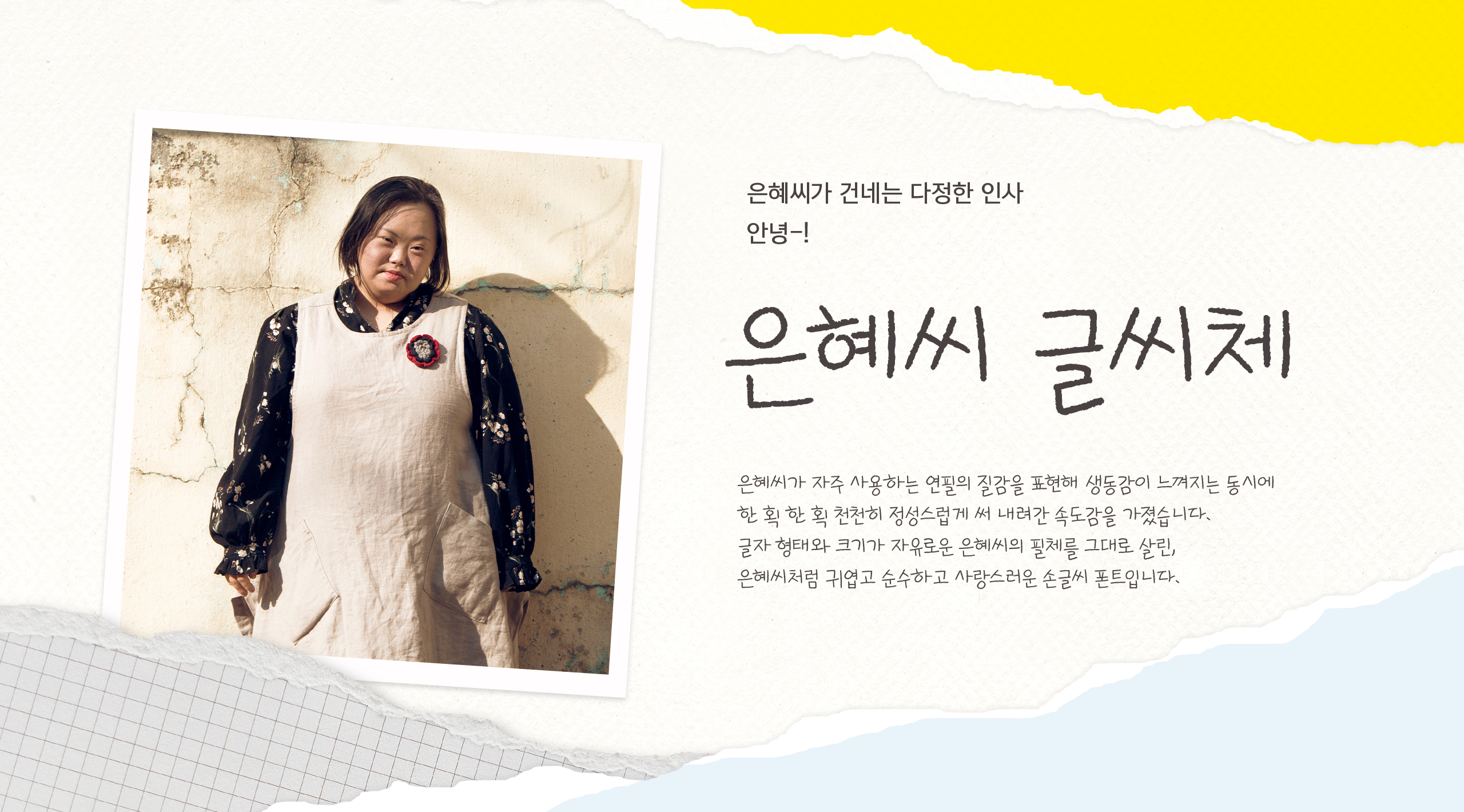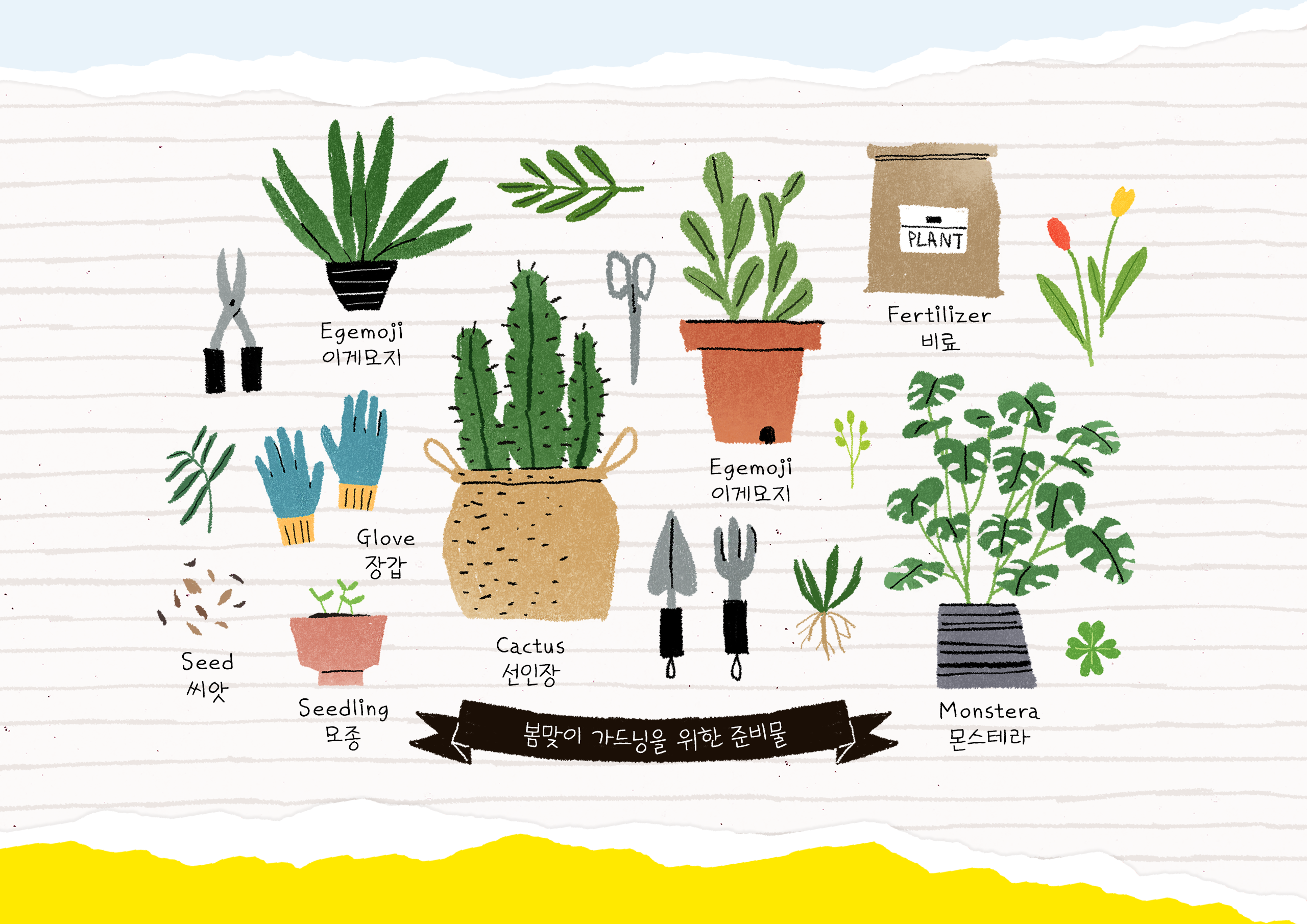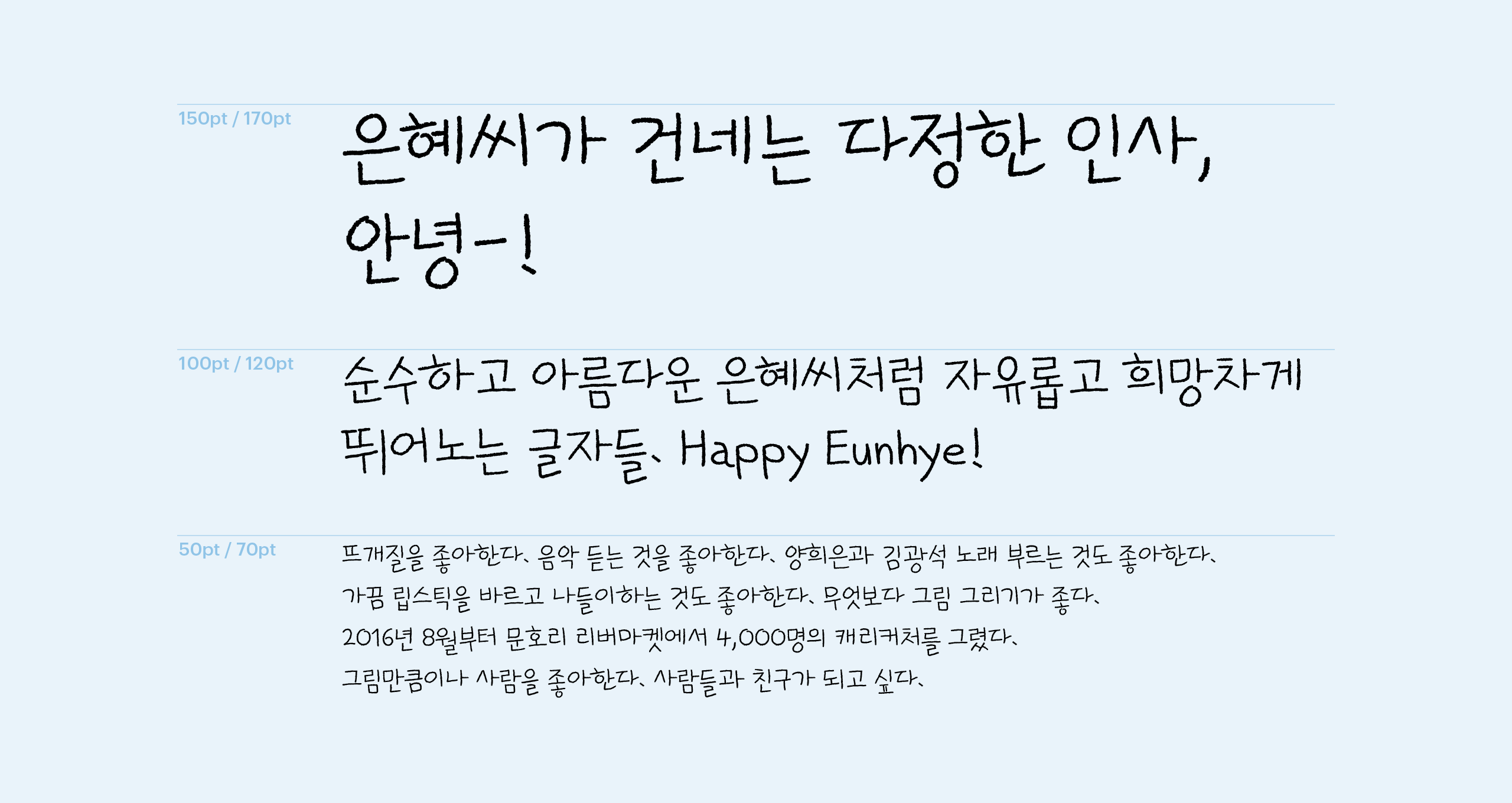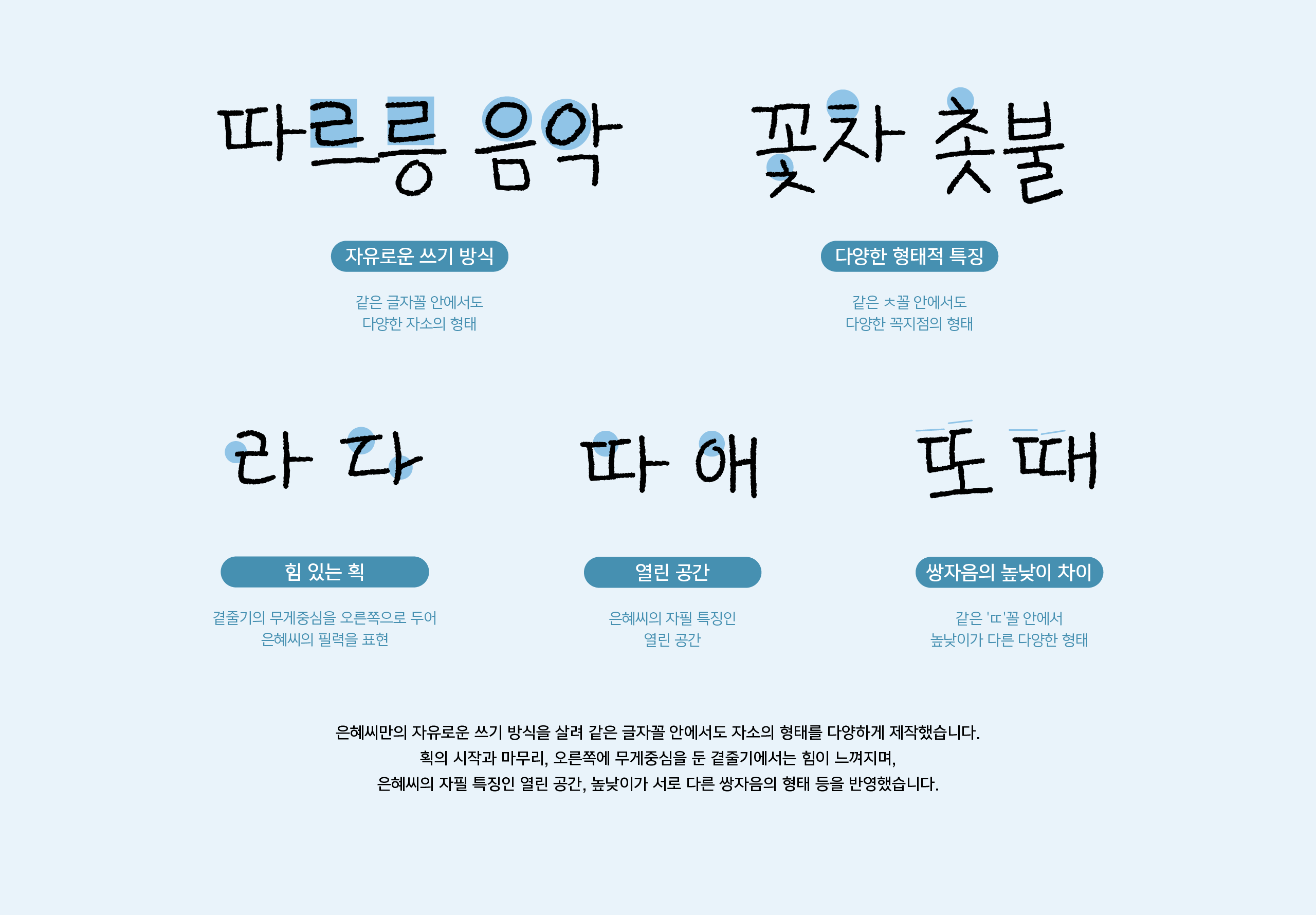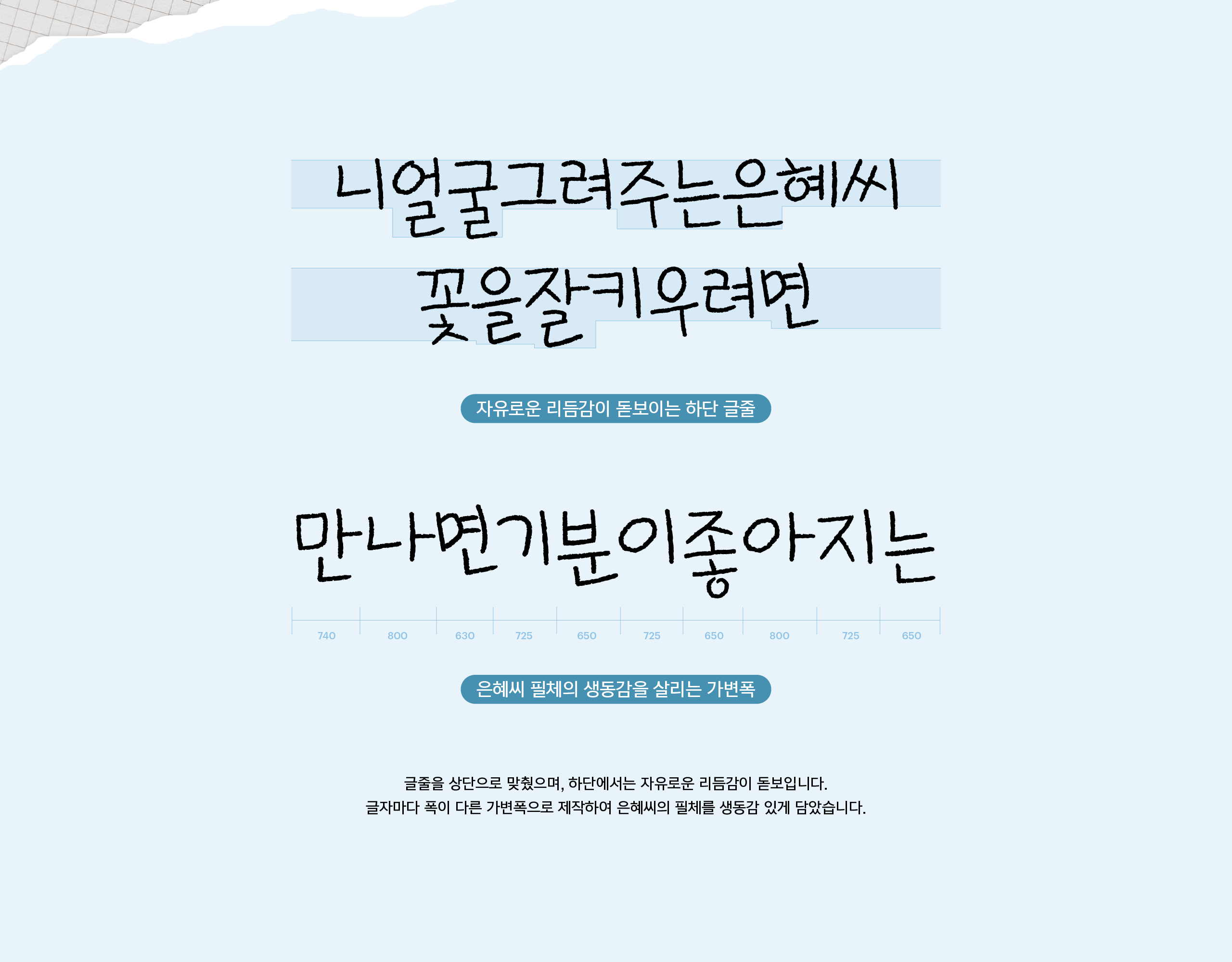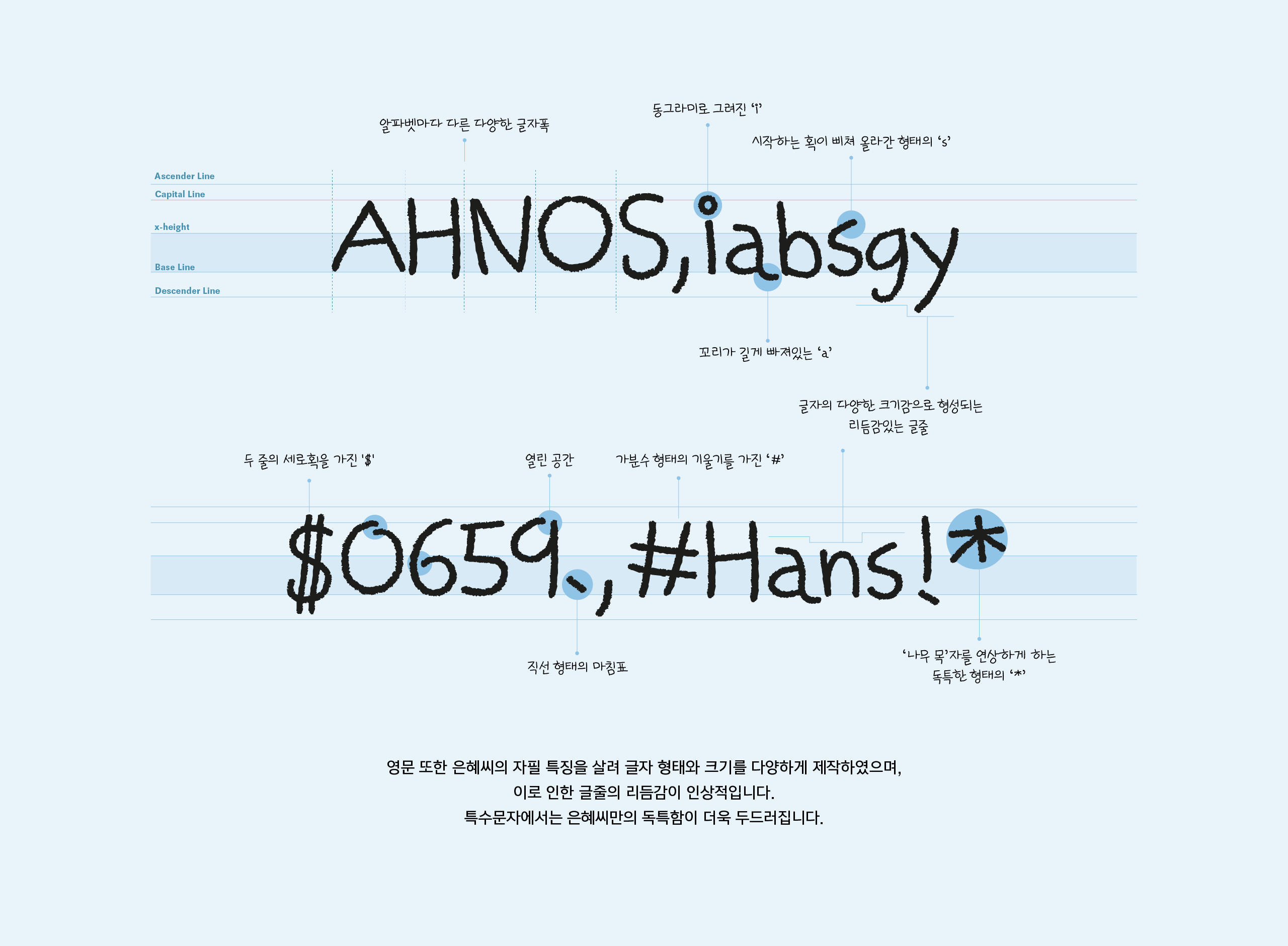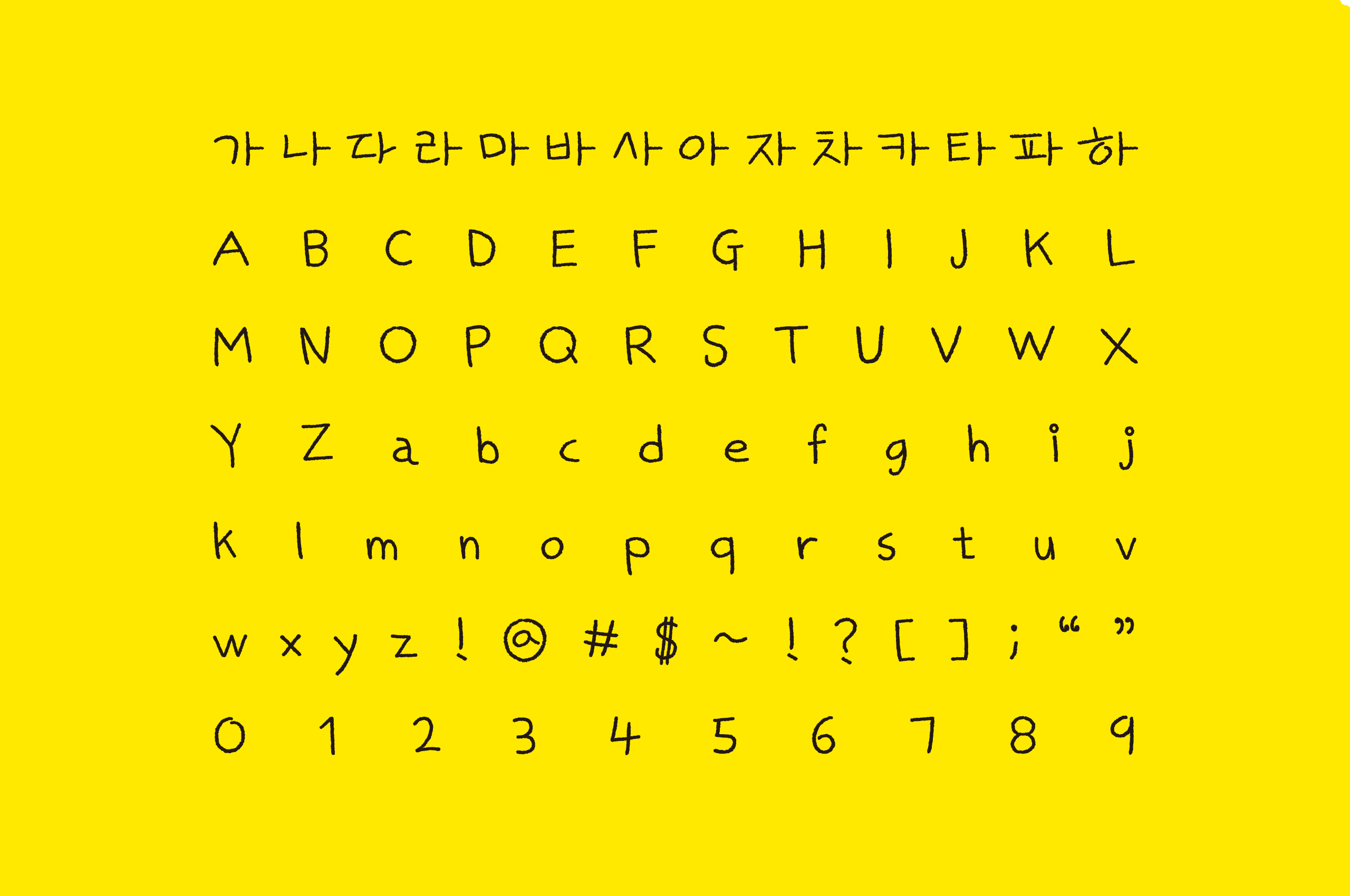
은혜씨 글씨체
Yoon 은혜씨 글씨체
많은 이들의 캐리커처를 그려온 미술 작가이자, 드라마 <우리들의 블루스>와 영화 <니얼굴> 등 배우로도 활동하고 있는 은혜씨의 손글씨 폰트입니다. 은혜씨가 자주 사용하는 연필의 질감을 표현해 생동감이 느껴지며, 글자 형태와 크기를 다양하게 제작하여 은혜씨만의 자유로운 필체를 그대로 반영했습니다.